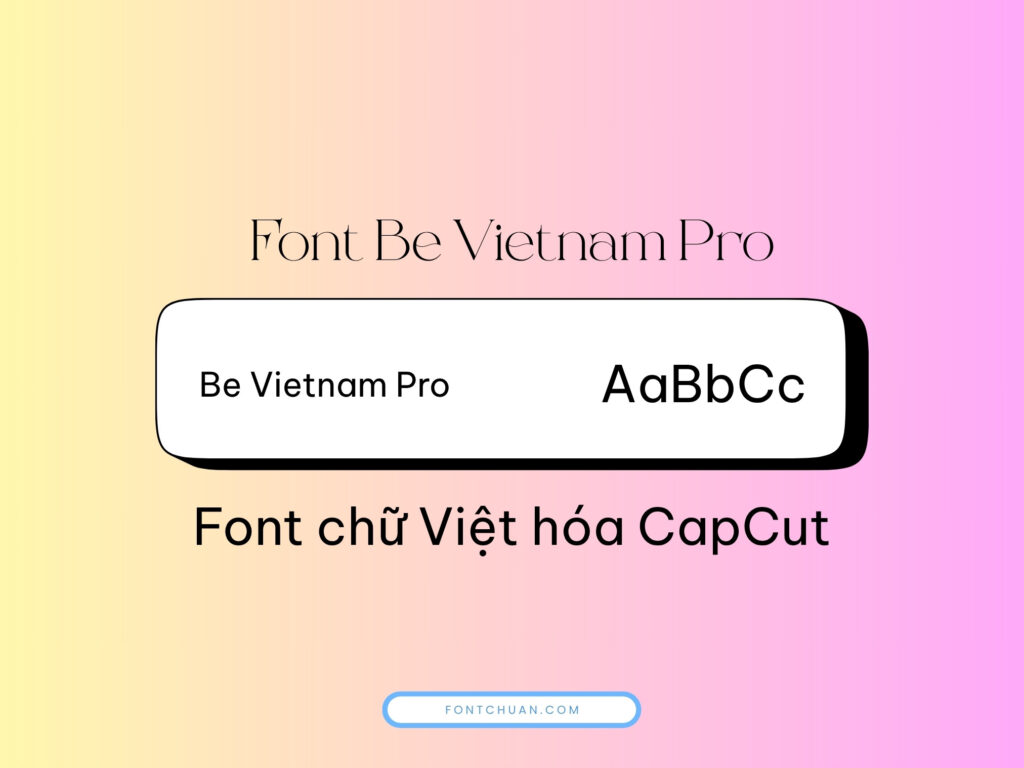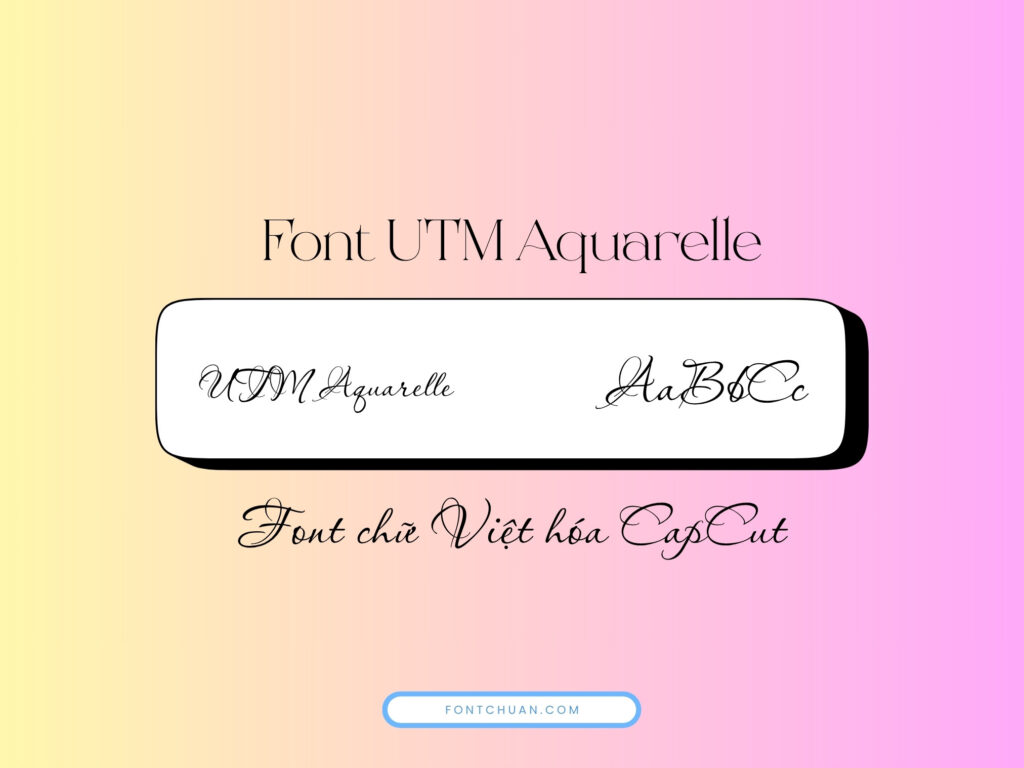
Bạn muốn làm mới video CapCut với những dòng chữ tiếng Việt đẹp mắt và ấn tượng? Kho font mặc định của CapCut thường đơn điệu, dễ lỗi dấu khi gõ tiếng Việt, khiến video kém chuyên nghiệp. Trong bài viết này, bạn sẽ khám phá bộ font chữ Việt hóa đẹp nhất cho CapCut năm 2026, hoàn toàn miễn phí, đa dạng phong cách giúp nâng tầm mọi sản phẩm sáng tạo của bạn!
Tại sao nên dùng font chữ Việt hóa khi chỉnh sửa video bằng CapCut?
Sử dụng font chữ Việt hóa trong CapCut không chỉ giúp video của bạn trở nên chuyên nghiệp mà còn mang lại nhiều lợi ích vượt trội:
Hiển thị tiếng Việt chuẩn
Font Việt hóa được bổ sung đầy đủ dấu và ký tự đặc biệt cho tiếng Việt, giúp văn bản trên video hiển thị rõ ràng, không bị lỗi ô vuông, mất dấu hay sai ký tự. Điều này đặc biệt quan trọng khi bạn muốn truyền tải thông điệp một cách trọn vẹn, tránh gây khó chịu cho người xem vì lỗi font.
Đa dạng phong cách chữ
Bộ sưu tập font Việt hóa cho CapCut ngày càng đa dạng, từ những font sans-serif hiện đại, trẻ trung đến các kiểu chữ viết tay nghệ thuật, vintage hoặc cá tính. Việc thêm font mới vào CapCut mở ra nhiều lựa chọn font style độc đáo, giúp bạn sáng tạo tiêu đề, phụ đề, trích dẫn hoặc bất kỳ nội dung nào trên video với dấu ấn riêng biệt.
Cá nhân hóa & thương hiệu
Lựa chọn font chữ phù hợp không chỉ thể hiện gu thẩm mỹ mà còn là cách xây dựng nhận diện thương hiệu cá nhân hoặc doanh nghiệp. Ví dụ, các vlogger thường sử dụng một font đặc trưng cho toàn bộ video để tạo sự nhất quán, dễ nhận biết với khán giả – giống như phong cách thiết kế trên Canva hay các nền tảng chuyên nghiệp khác.
Trải nghiệm người xem tốt hơn
Một video với phần chữ rõ ràng, đẹp mắt sẽ giúp người xem tiếp nhận nội dung dễ dàng, đồng thời tăng độ hấp dẫn cho sản phẩm sáng tạo. Phụ đề, tiêu đề hay trích dẫn sử dụng đúng font sẽ nổi bật hơn trên nền video, giữ chân người xem lâu hơn và góp phần nâng cao chất lượng trải nghiệm tổng thể.
Bộ sưu tập Font Chữ Việt Hóa cho CapCut đẹp nhất
Dưới đây là những font Việt hóa nổi bật, được yêu thích nhất khi chỉnh sửa video trên CapCut, phù hợp với nhiều phong cách từ hiện đại, viết tay đến cổ điển – giúp video của bạn luôn mới mẻ, ấn tượng và chuẩn tiếng Việt.
Phong cách Hiện đại & Tối giản (Sans-serif)
Lựa chọn hàng đầu cho video review, hướng dẫn, vlog đời sống hoặc các nội dung cần sự chuyên nghiệp, dễ đọc.
- Be Vietnam Pro: Font sans-serif quốc dân, tối ưu tiếng Việt, đa dụng cho tiêu đề, phụ đề lẫn nội dung chính.
- Montserrat Việt hóa: Hiện đại, trẻ trung, bo tròn nhẹ, nổi bật ở tiêu đề lớn hoặc caption ngắn.
- Roboto Việt hóa: Quen thuộc, tối ưu cho mọi kích thước màn hình, cực kỳ dễ đọc.
- SVN-Gilroy: Cao cấp, thanh lịch, nhiều kiểu đậm nhạt, phù hợp nhiều chủ đề khác nhau.
Phong cách Viết tay & Nghệ thuật (Handwritten, Script)
Tạo cảm giác cá nhân, gần gũi hoặc nghệ thuật; lý tưởng cho video du lịch, tâm sự, lyric hoặc kể chuyện.
- UTM Aquarelle: Viết tay như màu nước, mềm mại, bay bổng, rất “art”.
- SVN-Lemonade: Đáng yêu, năng động, cực hợp trend video vui vẻ, trẻ trung.
- Patrick Hand Việt hóa: Viết tay tự nhiên, mô phỏng nét bút thật, mang lại sự chân thành cho nội dung.
- VL Amelaryas: Script nghệ thuật, uyển chuyển, hợp lyric, intro hoặc quote nhẹ nhàng.
Phong cách Cổ điển & Sang trọng (Serif, Calligraphy)
Tô đậm sự nghiêm túc, chuyên nghiệp hoặc sang trọng cho video học thuật, lịch sử, thời trang, thương hiệu.
- Playfair Display Việt hóa: Thanh lịch, nét chữ có chân nổi bật, thích hợp tiêu đề video thời trang, phim tài liệu.
- UTM Times: Phiên bản Việt hóa của Times New Roman, cổ điển, quen thuộc, không bao giờ lỗi mốt.
- Lora Việt hóa: Serif cân bằng, dễ đọc, phù hợp cả đoạn text dài, tăng tính chuyên nghiệp cho phụ đề, mô tả.
Phong cách Trang trí & Ấn tượng (Display, Decorative)
Dành cho intro, outro, tiêu đề cần thu hút sự chú ý, tạo điểm nhấn cá tính.
- iCiel BC Cubano: Chữ in hoa đậm, mạnh mẽ, rất “hợp trend” cho video TikTok, intro ấn tượng.
- Baloo 2 Việt hóa: Bo tròn, vui tươi, cực kỳ nổi bật ở video giải trí, thiếu nhi.
- UTM Bebas: Display mạnh mẽ, dễ nhận diện, phù hợp call-to-action hoặc tiêu đề nổi bật.